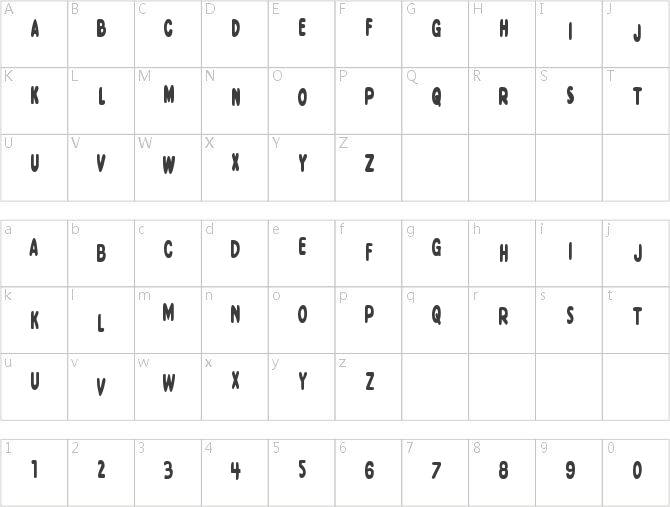
Excelsior-Comics-Condensed 詳情頁
Excelsior-Comics-Condensed字體字庫是一款讓人賞心悅目、百看不厭的英文字體,適合各類廣告和產(chǎn)品包裝設(shè)計應(yīng)用,字體大小0.04MB,格式為ttf字體,上傳用戶是Honor,作者/版權(quán)方為未知